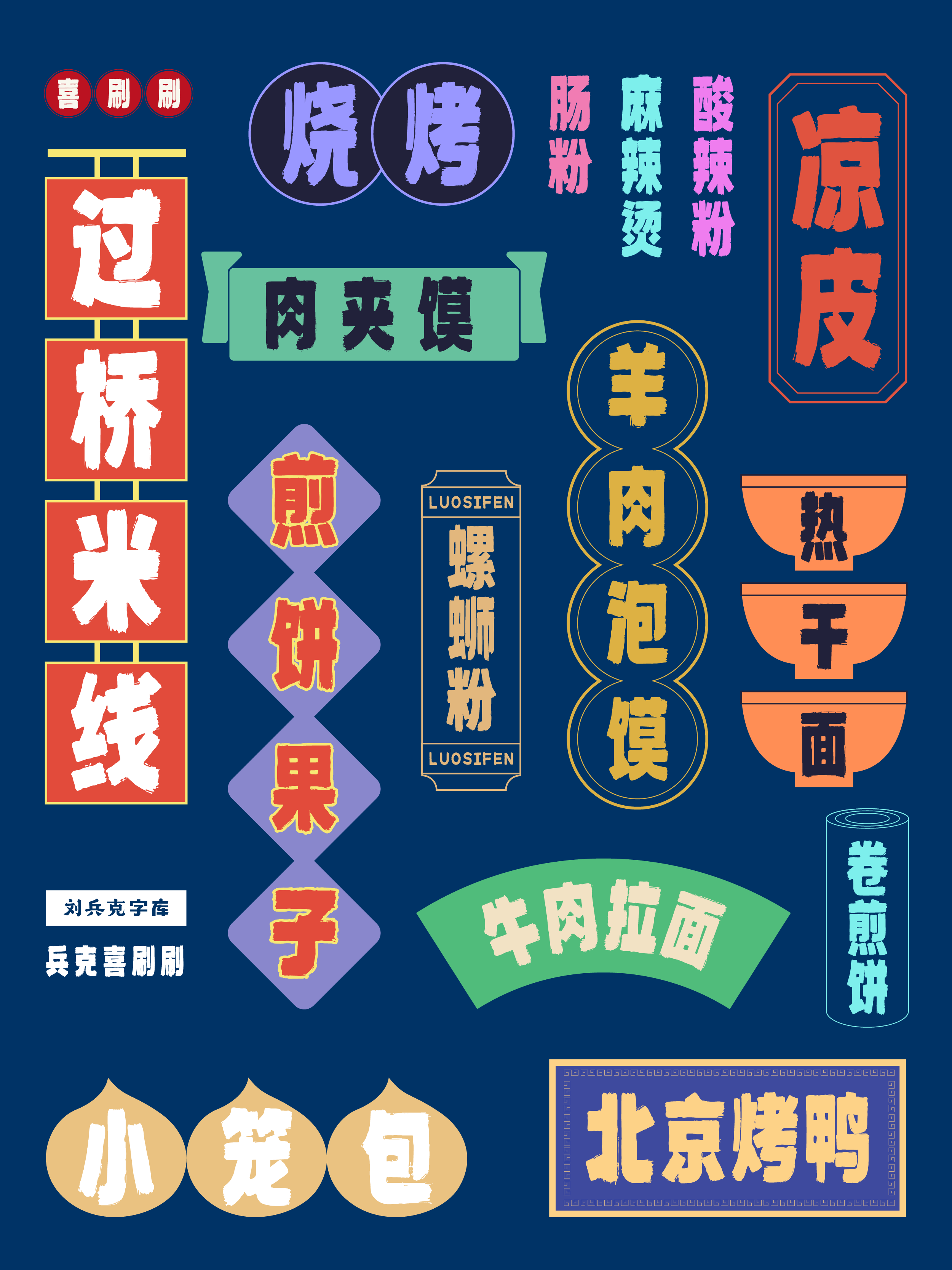
兵克喜刷刷
兵克喜刷刷,兵克喜刷刷,追求的是一种返璞归真、回归自然的美学境界。飞白笔触的巧妙运用,为字体增添了一种自然的韵律与动感,仿佛能听到笔尖在纸上滑动的沙沙声,感受到书写的快乐与自由。适合用于各种喜庆、欢乐的场合,也非常适合用于社交媒体等线上平台,作为个性化表达的一部分,能够展现出用户独特的审美趣味与生活态度。